【デンソーウェーブ】ハンディターミナル「BHT」にUCフォント搭載。「製品のプレゼンスを高める」フォントとの邂逅
2001年に設立された株式会社デンソーウェーブ様は、今や我々の生活に欠かせないQRコードを開発し、RFID(Radio Frequency Identification)と呼ばれる近距離無線通信を用いた自動認識技術やロボット事業、IoT事業領域にも取り組んでおります。「社会の生産性向上に深く、広く寄与し、人々の幸福に貢献する」という企業理念の下、モノづくり産業をはじめとし、広く社会へ新しい付加価値を提供しています。
そんなデンソーウェーブ様のハンディターミナル「BHT」シリーズにて、多言語において統一されたデザインコンセプトを持つ「UCフォント」を2021年にご採用頂きました。今回は、実際にフォントの選定や採用に関わられたデンソーウェーブの山下さん、藤坂さんに「UCフォント」をご採用頂いた理由、今後の事業展望などについて、オンラインにてお話を伺いました。
次世代型製品のコンセプトに符合した「瞬時に情報を正しく伝えられる」フォント
―― 山下さん、藤坂さん、本日は宜しくお願い致します!先ずは、お二人が所属されているAUTO-ID事業部のご紹介をお願い致します。
山下さん:デンソーウェーブはAUTO-ID事業、制御機器事業、ロボット事業の3つの柱で成り立っており、そのなかでAUTO-ID事業部は「自動認識」をキーワードに、効率化や働き方改革を推進する部署となっております。
1987年にリリースした世界初のバーコードハンディターミナル「BHT-1」はコンビニエンスストアや新幹線の移動販売など、バーコードを活用して販売管理や決済するような場面で長年活躍しており、自動認識のパイオニアとして業界をリードしてきました。
バーコードハンディターミナルの他にもQRコードを生み出し、RFIDにも注力しています。おかげさまで製造、流通、物流、医療など、幅広い業界のお客様に弊社製品をご愛顧頂いています。
藤坂さん:そもそも、そういった先進技術や製品は、デンソー、大きくはトヨタグループの製造現場でモノの流れを知りたいという「製造工程管理(かんばんシステム)」の観点が第一歩でした。
工程を管理するトレーサビリティ(※)へのニーズは、その後、製造現場だけではなく物流全体を支える領域まで広がっていき、現在はあらゆる倉庫や店舗などで情報集約を可能にするバーコードやQRコードが活用され、モノの流れが詳細に管理されています。
今回、御社のUCフォントを採用した「BHT」も、様々な作業現場で製品に付けられたバーコードやQRコードを読み取り、そのデータを管理システムへと繋ぐ役割を持った製品となります。
―― AUTO-ID事業部のご紹介、ありがとうございます。ハンディターミナル「BHT」について、もう少し詳しく教えて下さい。
山下さん:BHTの開発に着手したのは1985年頃ですね。1970年代からバーコードを読むだけのハンドスキャナーの開発をスタートし、広い倉庫内でのピッキング作業や、スーパーマーケット(バックヤード)での発注作業などでも対応できるように、ハンディ機器にデータを表示・記憶・送信するといった「コンピューティング」の概念を取り込んだ製品をやろうと決めてスタートしたのがこのBHTです。
BHTを実際に使用されるのは、倉庫の中で物品を持ち運びする方や、工場の組立ラインにいる方、コンビニエンスストアの発注・検品業務に携わる方などです。性別や年齢を問わず幅広いユーザーを対象とした製品になりますので、老若男女問わず、使いやすくあるべきだという想いを込めて開発されています。
―― 御社以外にもハンディターミナルを製造・販売する企業は国内外問わず多くありますが、BHTの優位性はどこにあるのでしょうか?
藤坂さん:製品のクオリティに最大限こだわっているところです。具体的には堅牢性ですね。倉庫やバックヤードなどの慌ただしい作業の中では、ぶつけたり落としたりということが日常茶飯事ですが、動かなくなったり壊れたりすると、業務が止まり、お客様にとっても大きな損失になってしまいますので、業務用機器メーカとして、非常にこだわっているポイントになります。加えて、読み取り性能の高さの部分で優位性を持っています。
また、当社独自OS「BHT-OS」を搭載した従来製品で使用中のアプリケーションを、画面レイアウト修正なしに移管できる「画面互換モード」を実装し、無駄のないシステム構造による安定した動作と、従来機種との高い互換性で、お客様のスムーズな導入・運用をサポートしています。常にお客様目線で、お客様に寄り添いながら一緒に製品を磨き上げてきたという自負が有りますね。
―― BHTへの理解が段々と深まってきました!今回、「BHT-OS」搭載の最新機種「BHT-S40」「BHT-S30」の両機に「UCフォント」をご採用頂きましたが、そもそもなぜフォントに着目されたのでしょうか?
藤坂さん:元々、BHTシリーズで使用していたフォントは使用開始から15年近く経過しており、世の中の目まぐるしい変化に対してどこまで対応出来ているんだろうという想いを抱いたのが基点です。
製品企画担当として現場を俯瞰するなかで、女性やシニア、海外出身の方など、働いている方々が多様化し、現場のスピード感、効率化への意識も大きく変わってきていると日々肌で感じていました。新しい時代の働き方にBHT自体が馴染んでいくようにしたい、あらゆる方に使いやすい製品にしていきたいというところを考慮して、次世代型として開発中だった「BHT-S40」「BHT-S30」のコンセプトに「使いやすさ」を置いたところから、フォントにも意識が行くようになりました。
―― なるほど。働き方の変容に即したコンセプト設計を行ったのですね。
藤坂さん:はい。その上でBHTの画面サイズは、2.4~3.2inchとコンパクトです。お客様の持ち運びやすさの観点からは非常に喜ばれますが、多くの情報を表示させようとすると必然的に小さい文字になりやすく、結果として見づらくなることに課題を感じていました。
また、商品型式や、製造現場の部品型番など、数字と英語が混在するものを扱うケースも多いのですが、その際、数字の0とO(オー)、1とI(アイ)などの見間違いはトラブルに繋がりますので、文字の形状判別も大きな課題でした。
山下さん:BHTを使用されるお客様のなかには、一日に一人で千個以上の荷物を取り扱うような繁忙な倉庫現場もあります。瞬時に画面を判読することがスムーズな作業に繋がりますし、移動を伴う作業をされている方も多く、画面の確認は出来るだけ短いことが望ましいんです。また、画面の見間違いにより誤出荷や誤発注などを引き起こし、会社に損害をもたらすケースも考えられます。
そのため、「瞬時に情報を正しく伝えられる」フォントの搭載が次世代型製品の必要条件のひとつでした。そこで浮上したのが、ユニバーサルデザインのコンセプトを持ったフォントだったんです。
「UDフォントを定量的に捉える取り組み」、その説得力が会社を動かす契機に
―― ハンディターミナルに対する課題感と、その課題感を前提としてユニバーサルデザイン(UD)のコンセプトを持ったフォントに着目した流れが明瞭になりました。そこからのプロセスについて、是非詳しくお聞かせ下さい。
藤坂さん:「BHT-S40」「BHT-S30」に搭載するフォントはUDコンセプトで進めると決めた上で、課題はデザインとコストでした。見た目は勿論のこと、どのくらいの費用で進められるのかが全く掴めない。ただ、先ずはデザインの観点から調べていこうと決めて調査を開始したら、フォントワークスのUDフォントに関するWebページが、非常に納得感あったんです。
―― どういったところが、藤坂さんの琴線に触れたのでしょうか?
藤坂さん:UDフォントを「視認性」「可読性」「判別性」というキーワードに分けて、それぞれに対して定量的に捉える取り組みを非常に大事にされていたところです。
UDって、定量的に捉えることが難しいと感じていました。上司を説得する上で、どういう風に良さを伝えたら良いんだろうと悩んでいたときに、御社のWebページに出会いました。
私自身、エンジニアとして当社に入社して、その後製品企画課に異動しましたが、UDフォントを定量的に捉えるというところを大切にしていて、非常に説得力が有りました。また、国際ユニヴァーサルデザイン協議会の実施するIAUDアウォードを受賞を受賞していることも知り、ユニバーサルデザインに対する取り組みの真剣さが感じられ、御社フォントの導入を本格的に考え始めました。
Webページのエビデンス資料をダウンロードして、稟請の際に活用したことを覚えています。最終的には、当時の営業担当の方にコストの相談にも柔軟に乗って頂いたことも大きかったですね(笑)。
―― 嬉しいお言葉、ありがとうございます!その他、決め手となったところはありましたでしょうか?
藤坂さん:当時の営業担当の方に多言語対応の課題と、フォント容量の課題に対するソリューションを併せて提案頂いたことです。
―― その点、是非詳しく教えて下さい。
藤坂さん:BHTは仕向先の関係で、多くの言語を必要としています。現地で作業される方が使用する機器なので、現地語でないと作業できないケースが多いんです。
その課題に対して、UDコンセプトの日本語フォントをベースとして統⼀されたデザインコンセプトを持つ、読みやすい多言語フォント(UCフォント)を提案頂きました。その上で、タイ語、アラビア語、ヘブライ語などの複雑な表⽰ルールを持つ⾔語を、組み込み機器上で正しく表⽰するための「レイアウトエンジン」もセットで提案頂きました。この辺りの迅速、かつ当社要望に沿った対応は、大変心強かったですね。
後者に関しても、WindowsやAndroidといった汎用OSで使うようなフォント群は容量の関係で「BHT-OS」には実装が難しいと分かった際に、書体辺りの収録文字が多く容量の大きい日本語、中国語(簡体字・繁体字)に関して「軽量フォント」を直ぐに提案頂いて、もうこれしかない!と思いました。
―― 藤坂さんからの稟議を決裁する立場の山下さんは、藤坂さんからのご相談をどのように捉えていらっしゃいましたか?
山下さん:個人的には、時代にマッチしていていいかな、くらいの思いでしたが(笑)、 実際に藤坂が実施していた業務画面イメージの内容を、作業者のように一瞬で確認するという評価に参加してみたところ、認識しやすさに差があることを実感しました。 特に、フォントサイズが小さくなった場合や、英数字においてはその差が大きく感じられ、 「これは絶対に現場に必要!」という思いになりました。
また、他拠点で検証に参加した当社の営業担当からは「丸みの具合が綺麗」「今っぽい雰囲気」 という意見も多く出てきて、「綺麗さ」「新しさ」といった面でも優れていることがわかり、 途中から藤坂と強力に推進しました(笑)。
何より、こういった現場目線の新しさというのが、製品のプレゼンスを高め、結果として当社のファンを増やすことにつながるということに私自身気が付きました。 UCフォント選定のプロセスは、私にとっても貴重な学びの機会となりました。
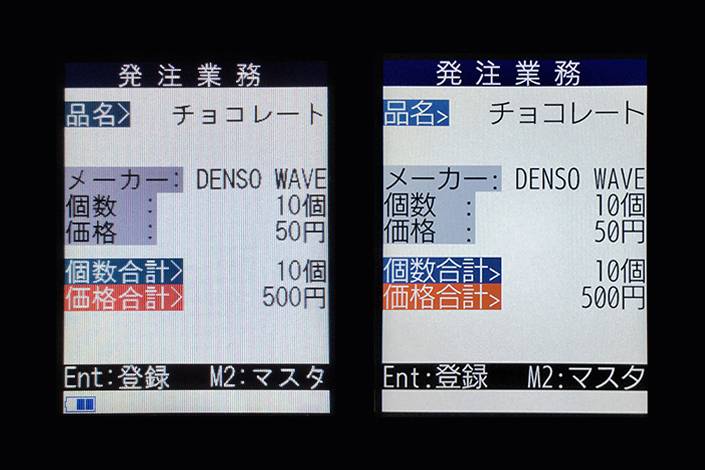
「人」中心の製品をこれからも生み出し続ける!
―― 御社でのUCフォント採用の経緯について、詳細を教えて頂きありがとうございました。最後に、御社事業の今後の展望についても教えて下さい。
藤坂さん:今後の社会動向や課題(人手不足)を考えると、我々の製品はより一層使命を増すと感じており、同時にUDも欠かすことのできない考え方になると思います。これから先もあらゆる人に使いやすい製品を追求・開発していきたいと考えています。
山下さん:当社の企業理念は「社会の生産性向上に深く、広く寄与し、人々の幸福に貢献する」であり、生産性向上には人が使いやすいことが不可欠だと考えています。当社ではこれからも、この企業理念をプロダクトデザインに落とし込み、「人を中心においた」製品を生み出し続けることに全力を尽くしていきます。